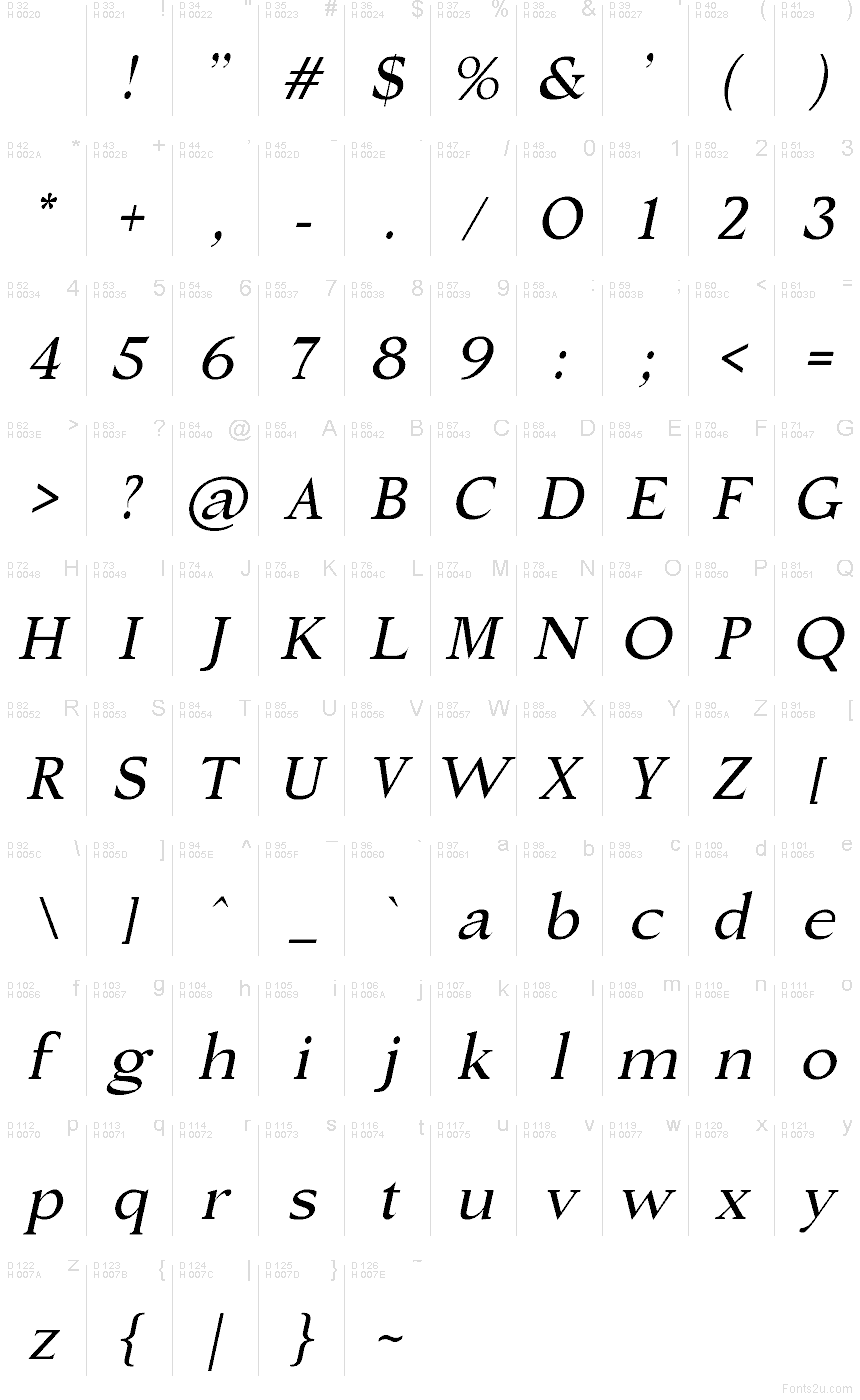
Il carattere Silent Citadel Light Italic, creato da Muhamad Fikry Nuralif di Fikryal Studio, conferisce un tono composto e letterario alla famiglia Silent Citadel. È un font serif gratuito dal tocco leggero: tratti nitidi, spaziatura ariosa e un flusso corsivo che ricorda l'inchiostro che scorre rapidamente su carta liscia, senza risultare eccessivo o pretenzioso.
Silent Citadel Light Italic dà il meglio di sé in citazioni editoriali, pagine di poesie, lookbook di moda, titoli di film, branding per boutique, inviti eleganti e brevi descrizioni di prodotti sulle confezioni. Usalo in dimensioni leggermente più grandi (con un interlinea generoso) per far respirare l'inclinazione, e abbinalo a un font sans serif pulito per didascalie e navigazione: questo font gratuito rimane raffinato senza passare inosservato.